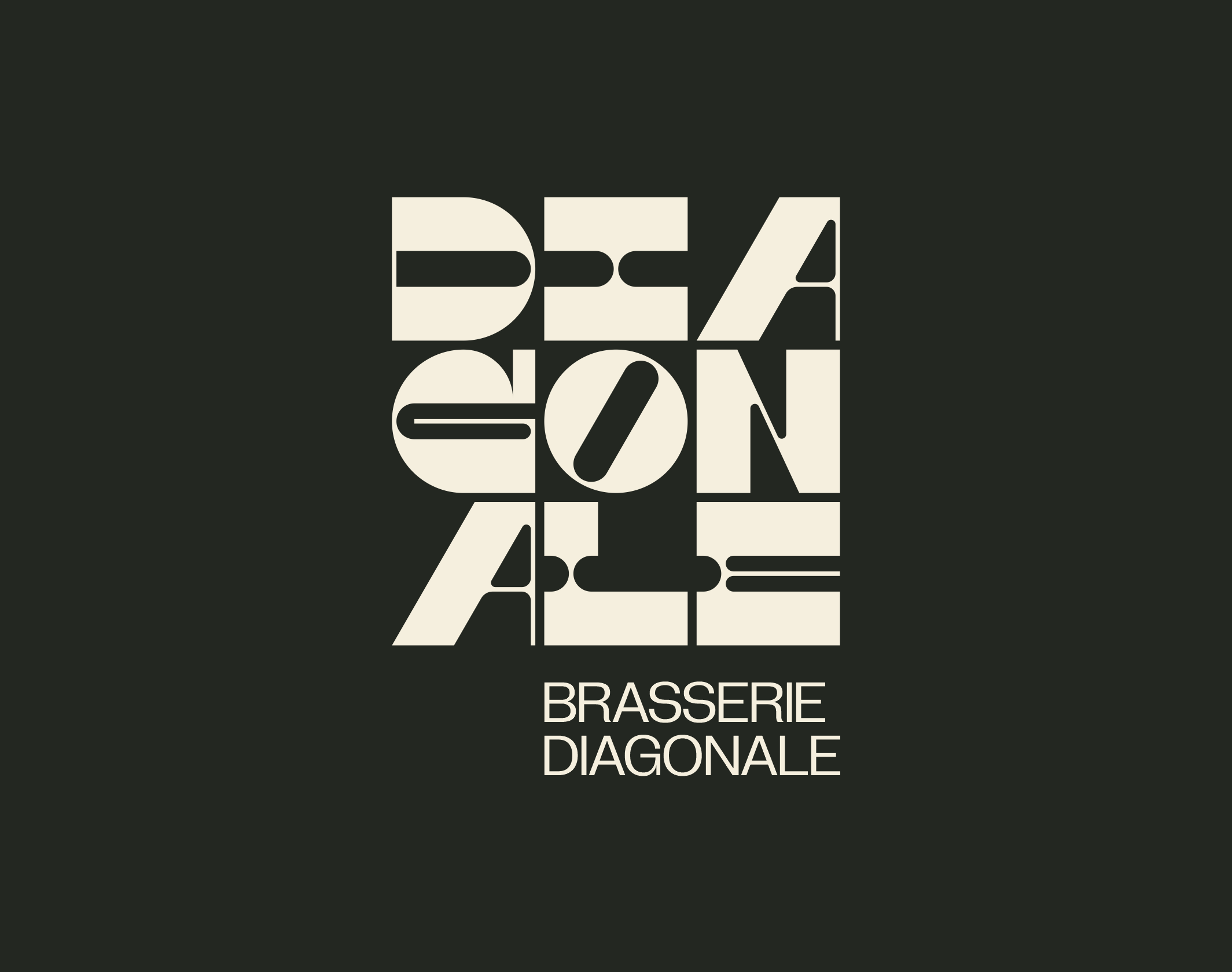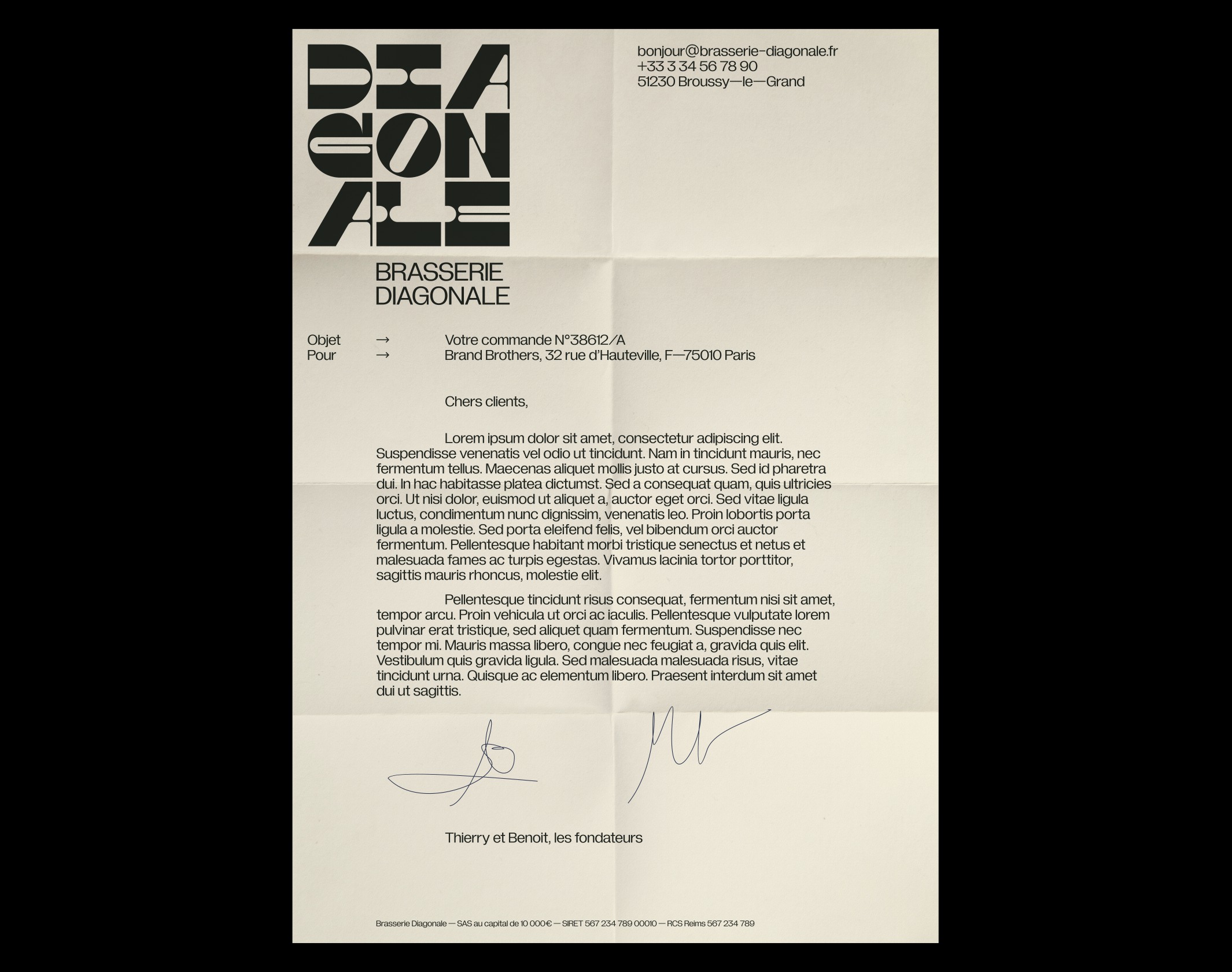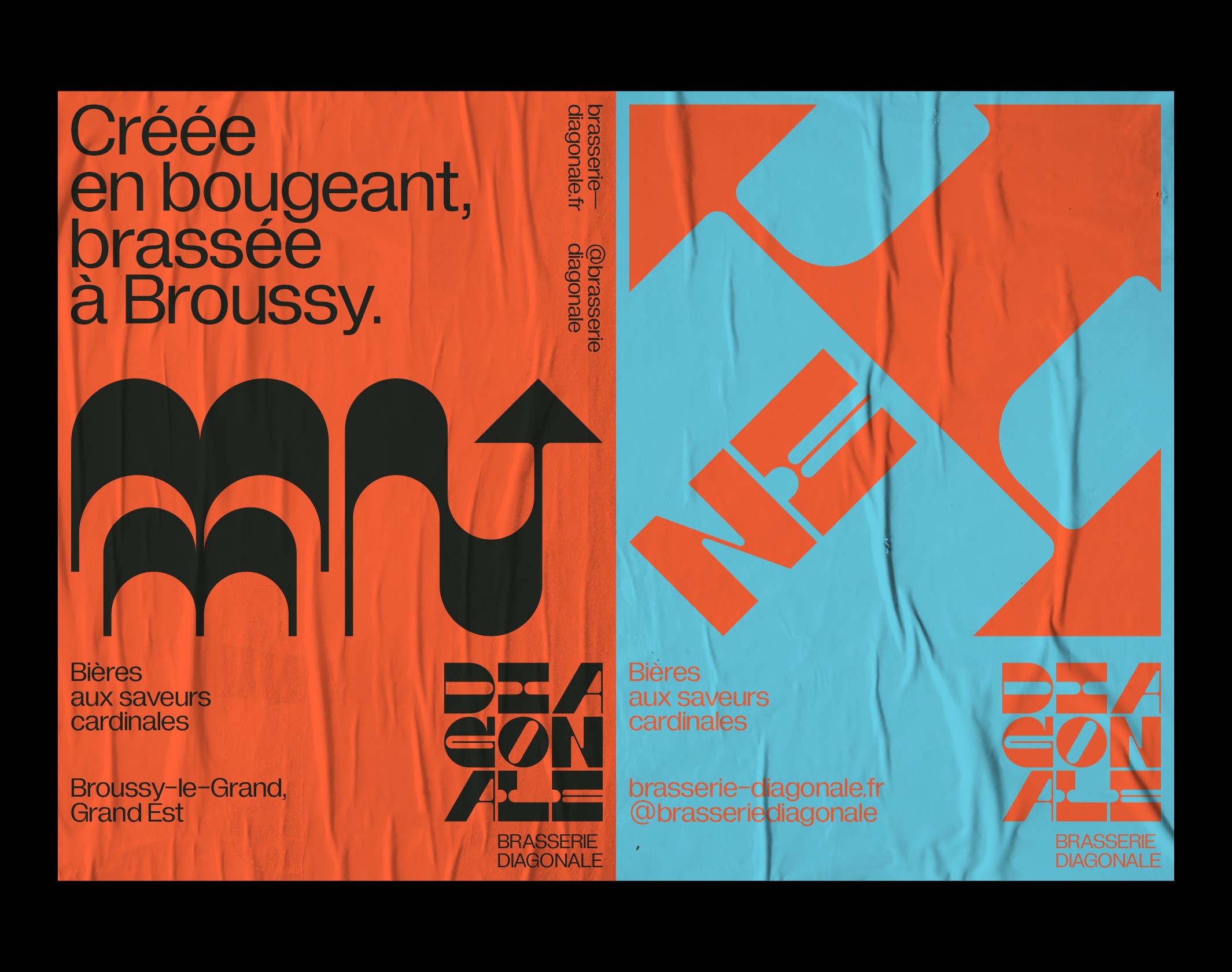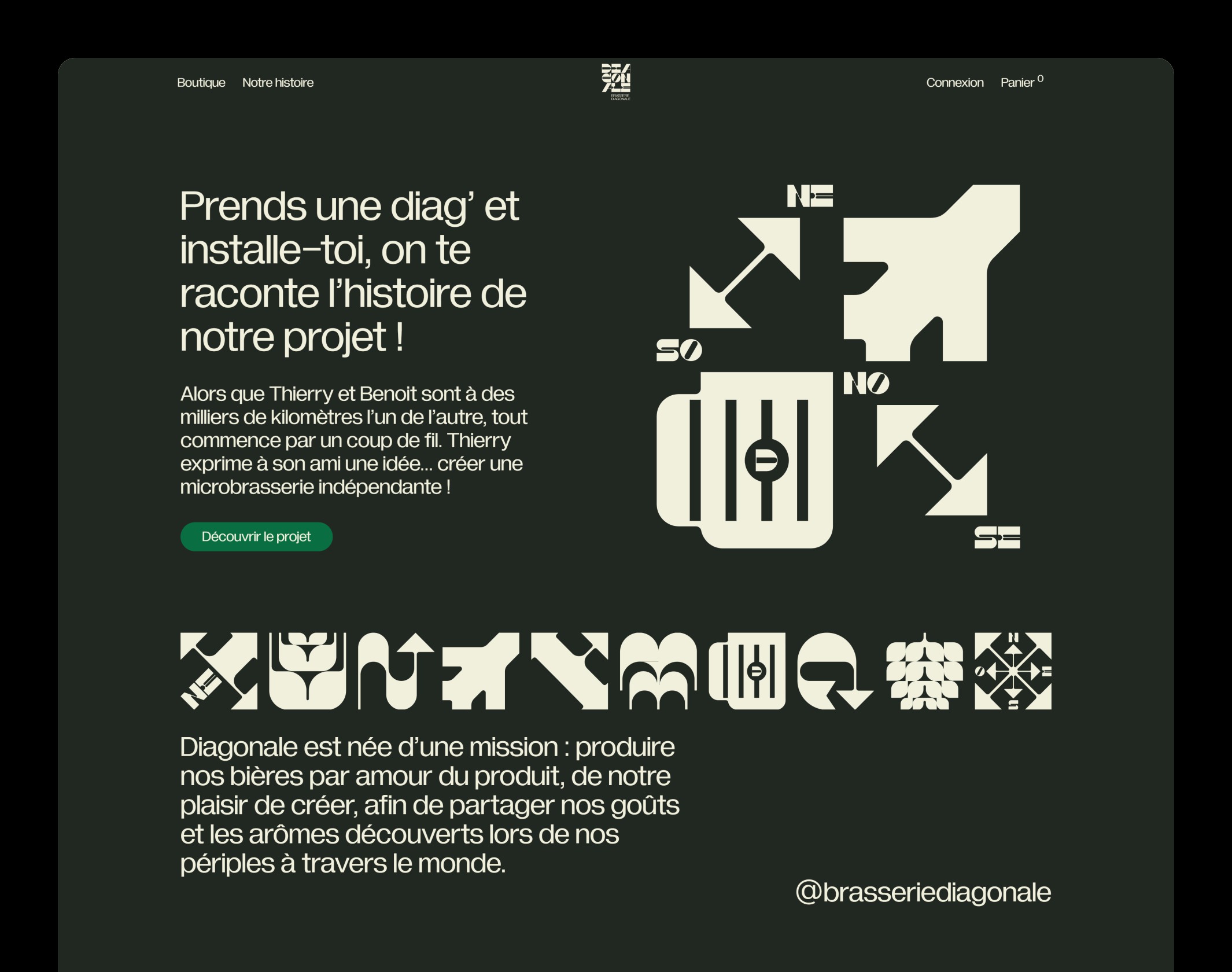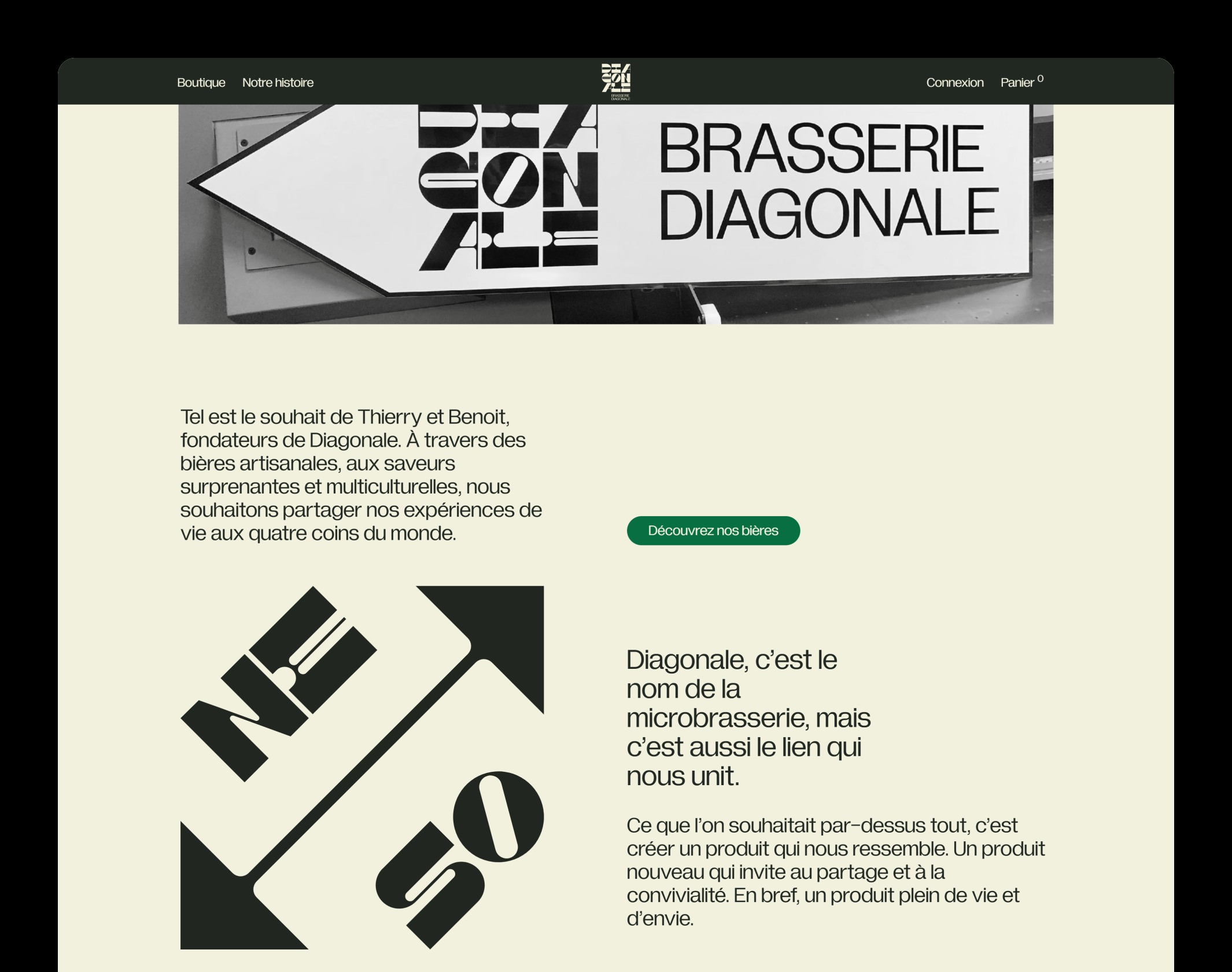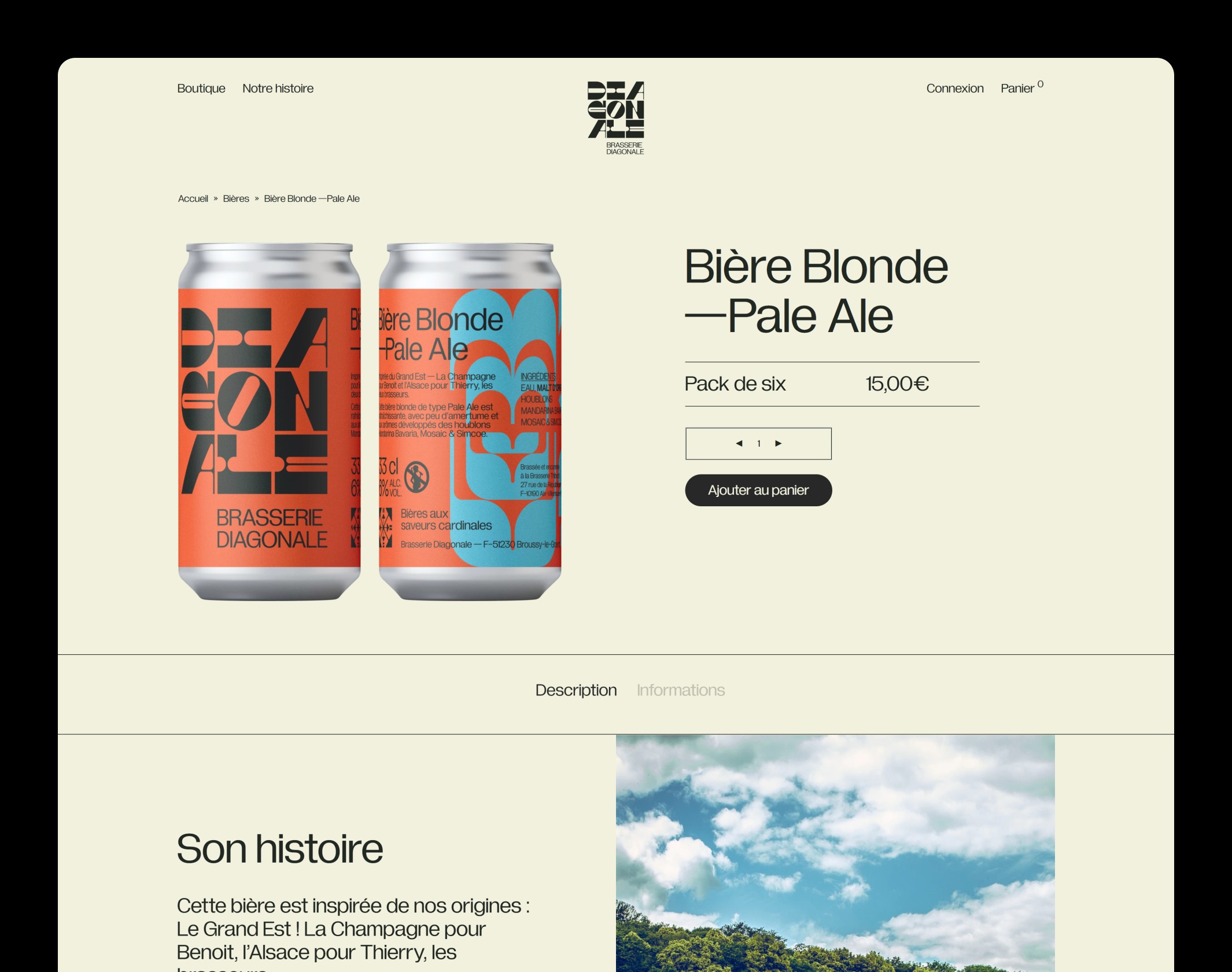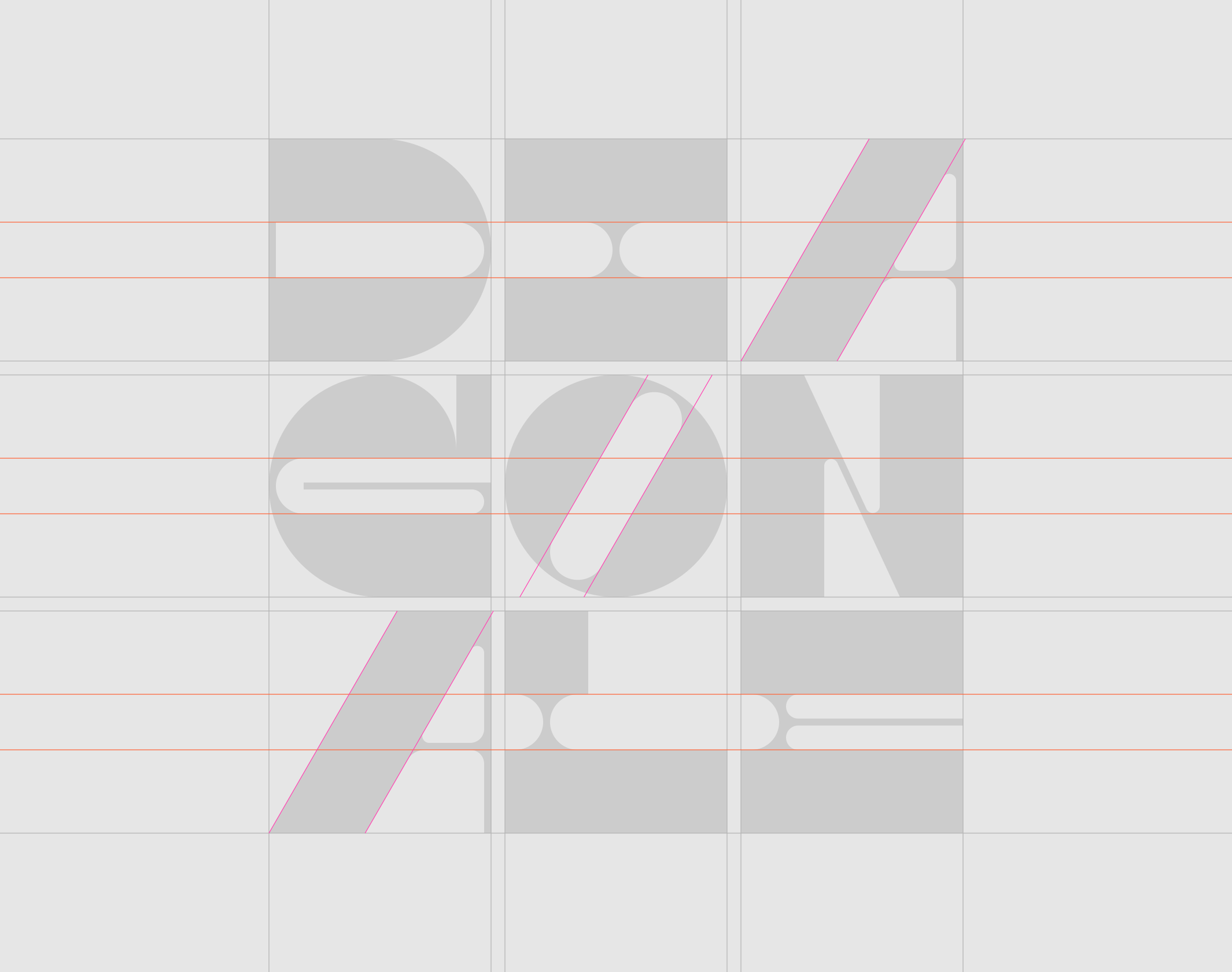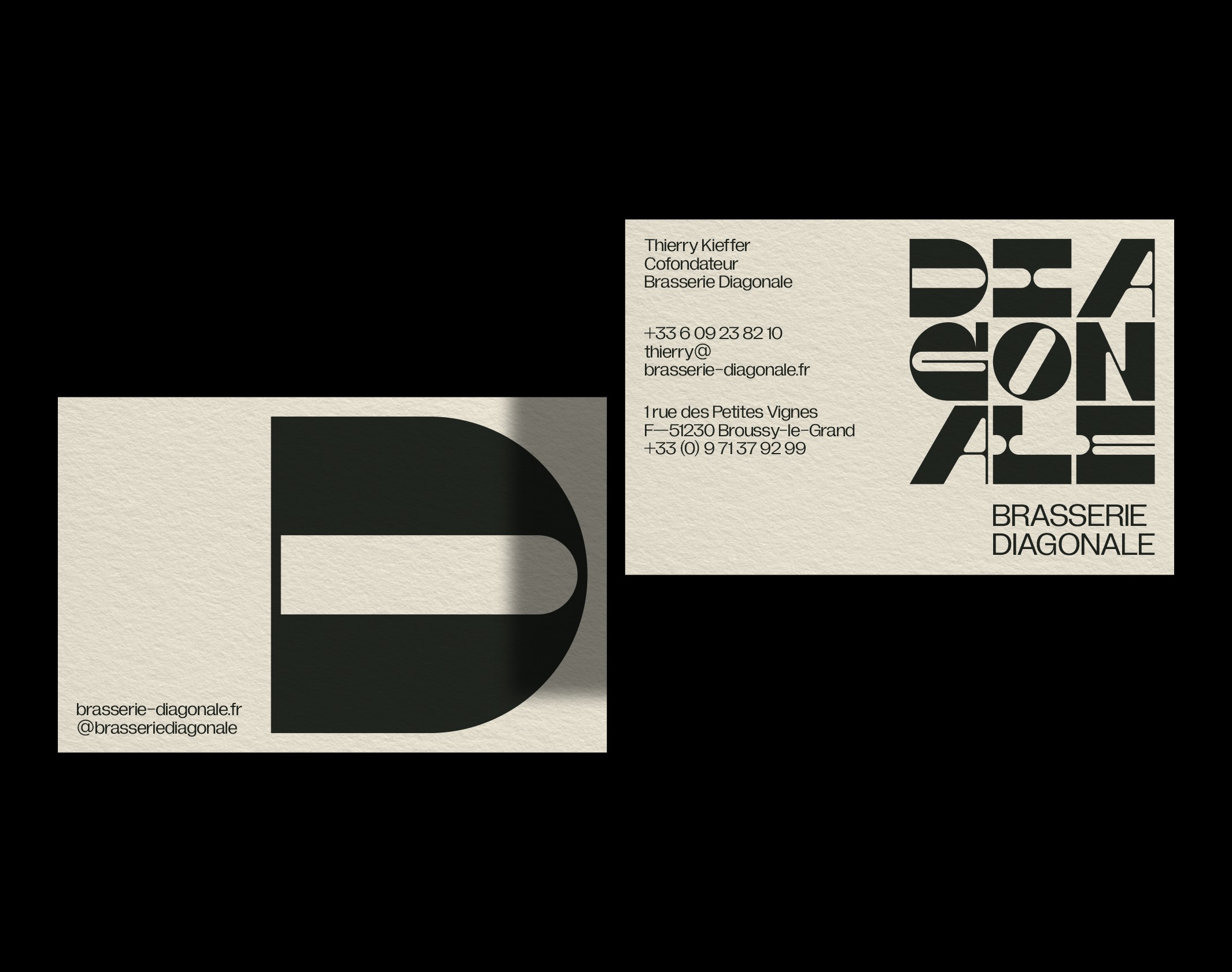
Brasserie Diagonale
La Brasserie Diagonale allie passion et créativité à travers une identité visuelle unique qui célèbre les trajectoires de vie de ses fondateurs.
La Brasserie Diagonale est née de l’imagination de Thierry et Benoit, amis de longue date dont les carrières respectives les ont amenés à sillonner le globe. Revenus dans le Grand Est, l’idée de créer une micro-brasserie indépendante à Broussy-le-Grand (Marne) germe alors en 2019, avec pour objectif de faire partager dans des bières artisanales les trajectoires de vies singulières des deux fondateurs. Fin 2020, Brand Brothers se voit confier l’identité visuelle intégrale du projet.
Notre proposition graphique tourne autour d’un langage typographique et symbolique très étendu. Le logotype, composé de caractères aux contrastes inversés très prononcés, dessiné spécialement pour l’occasion, sert de base à une collection de glyphes qui enrichissent considérablement la narration et l’imaginaire autour des bières Diagonales. Conçus à la manière des Dingbats, ces symboles permettent des composition variées, formant une ossature graphique simple et puissante. Associé au caractère Gramatika (Typefaces of the Temporary State), ce langage visuel se développe ainsi sur les deux premières canettes de la marque, un site marchand conçu au studio et des séries de posters. La collaboration entre Diagonale et Brand Brothers se poursuivra au fil des sorties de nouvelles bières, permanentes ou éphémères.